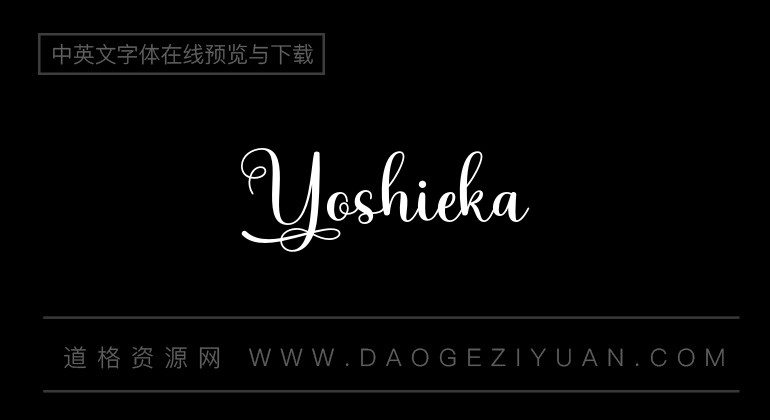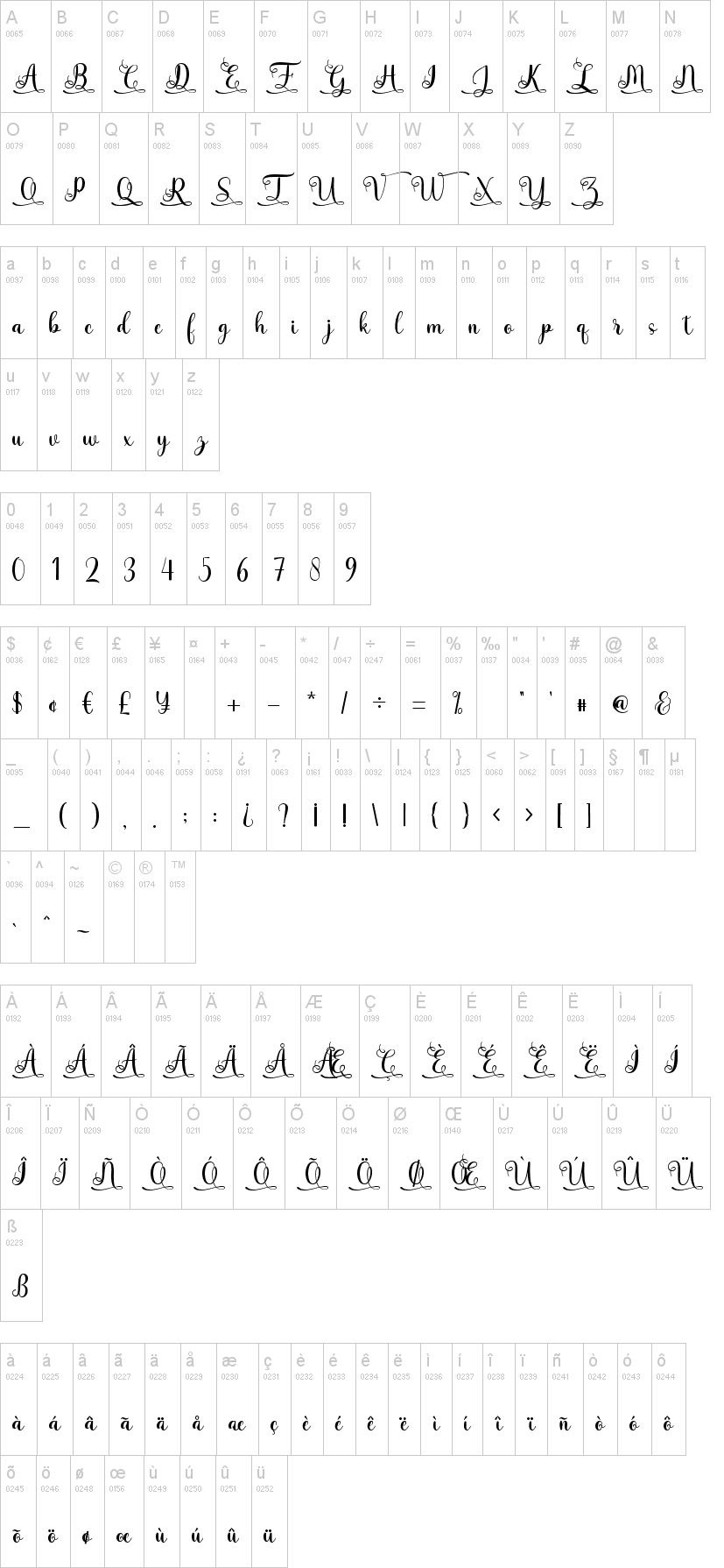
? Yoshieka 字体是一款日本美术字体,由著名的日本字体设计师Yoshieka Kato设计。它结合了日本传统文化和现代感,是一款多功能、灵活的字体。它有丰富的细节,可以用于绘画、插图、标志和文字等多种设计应用,是一款适用于多种场景的字体。内容介绍
Yoshieka是一款非常不错的手写艺术字体,具有很好的视觉感,适合于文化类的宣传设计、商业类品牌的广告和产品包装设计以及个性化文字排版等较多场景。